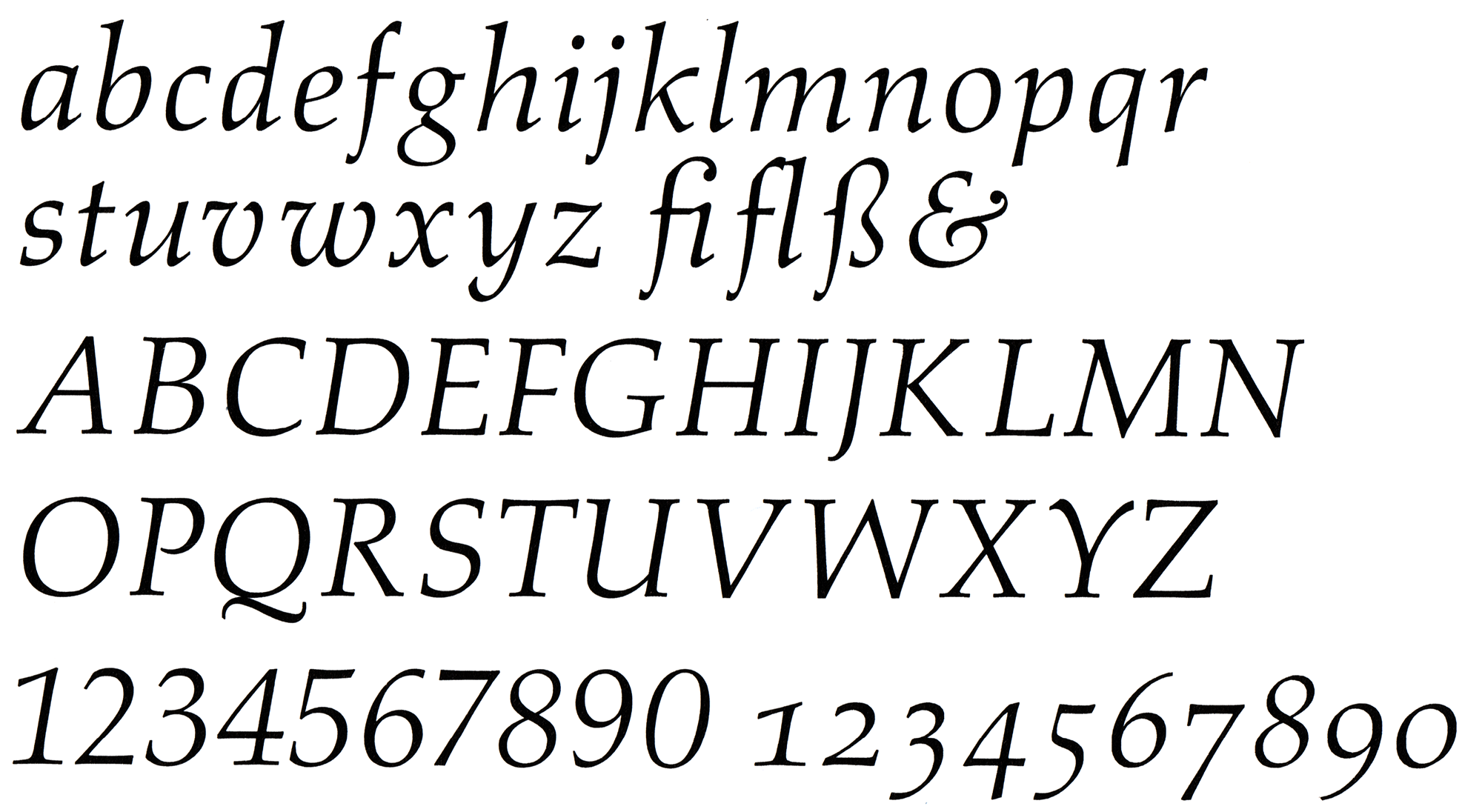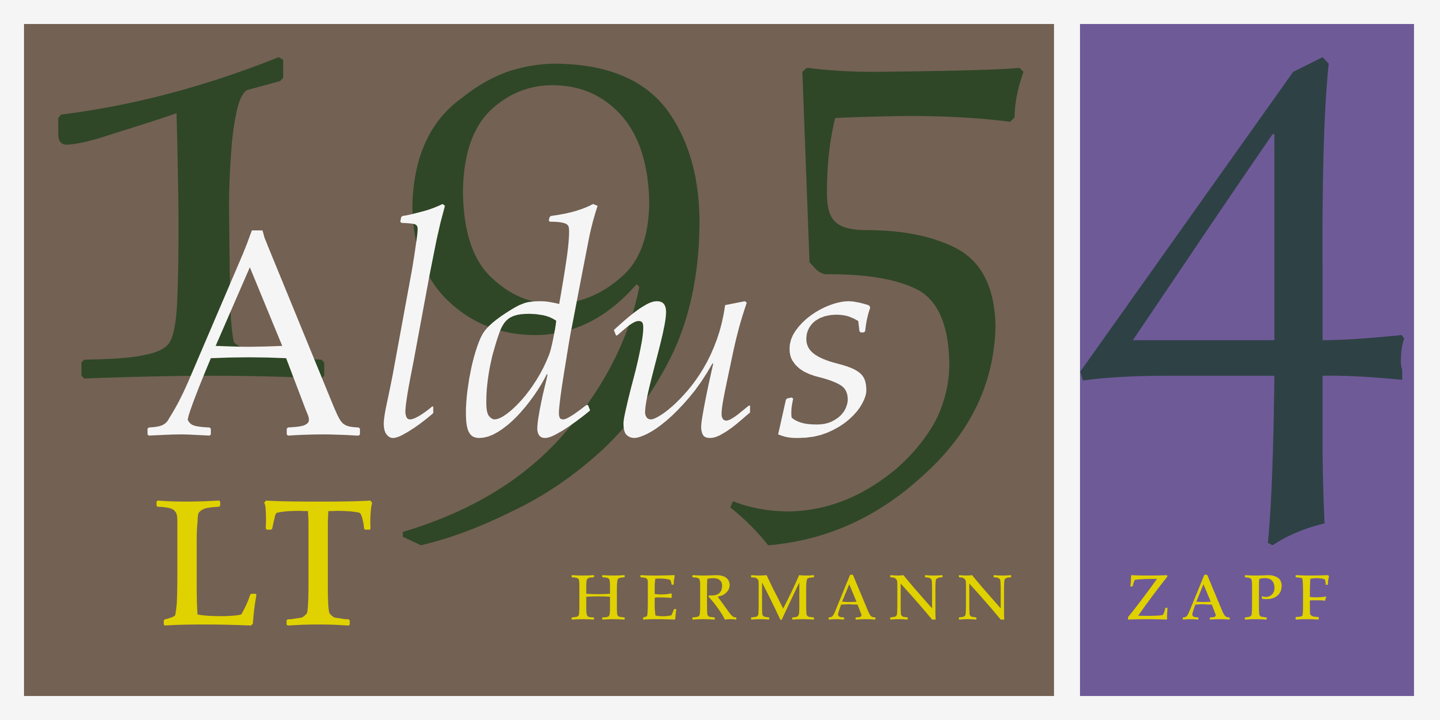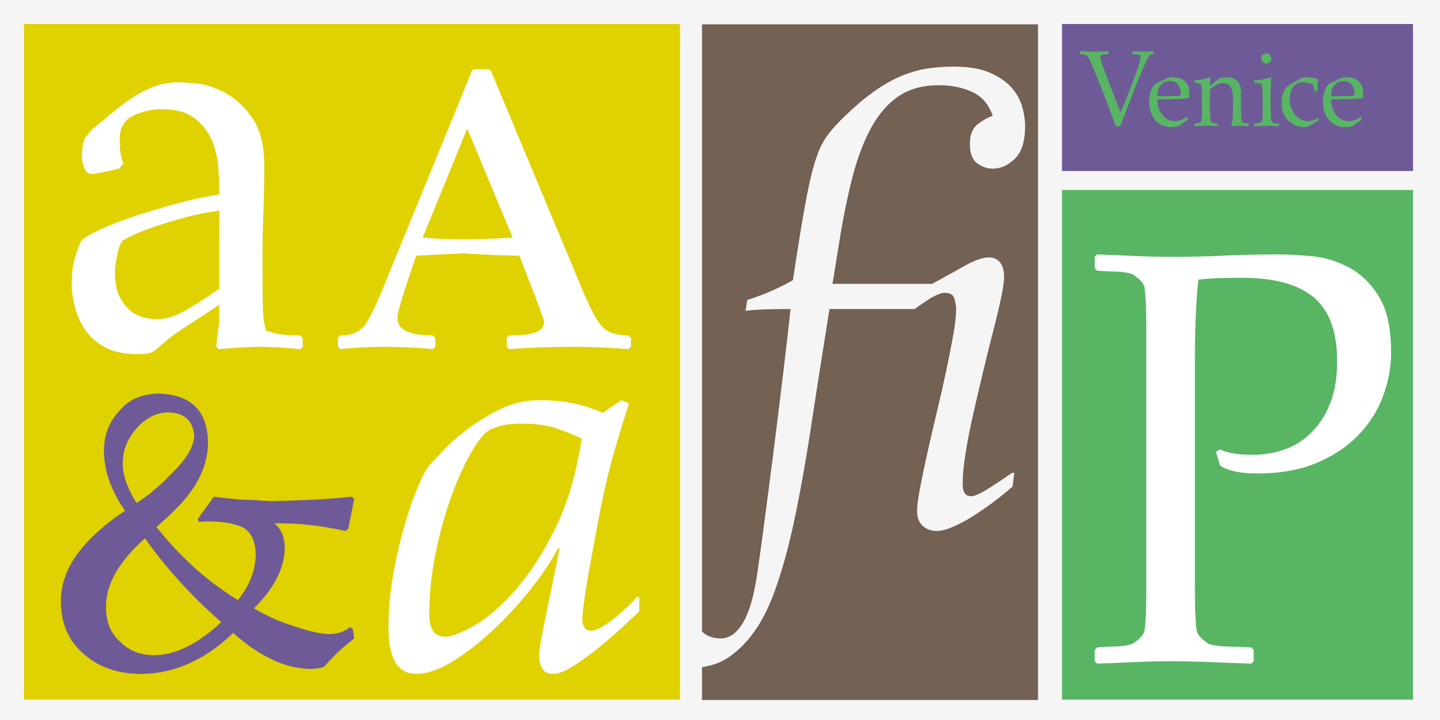
- 1954
- Antiqua humanistisch
Die Aldus von Hermann Zapf ist ein Ableger der zuvor erschienenen Palatino und wurde mit leichteren Strichen und offeneren Formen speziell auf die Anwendung in Büchern hin optimiert.
Die Schrift erschien in einem aufrechten und kursiven Schnitt im Bleisatz und später als Fotosatzschrift. Mit der digitalen Neuauflage als Aldus Nova gibt es jetzt auch eine gut ausgebaute Version mit zwei Strichstärken.